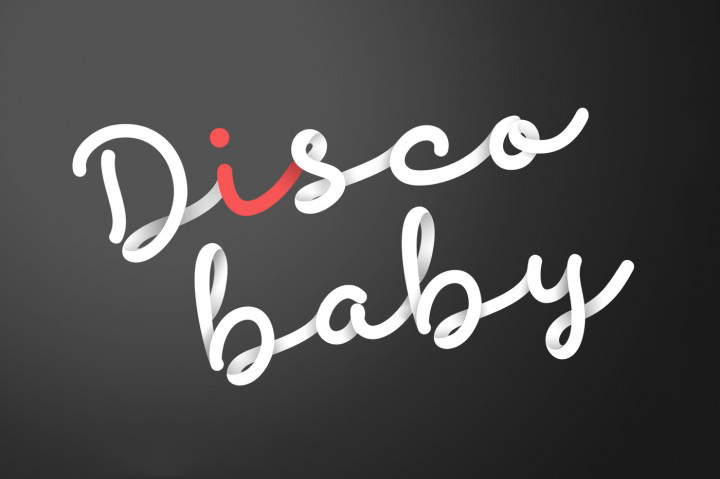
Discobaby Script Font – Download Grátis
A Discobaby Script Font é uma escolha perfeita para quem procura uma fonte script que traz aos designs um toque jovial e encantador sem perder a elegância necessária. Inspirada na forma quase infantil com que os pequenos escritam, essa fonte consegue criar um entusiasmo irresistível em qualquer design. Seja para o packaging de alimentos ou uma assinatura, desde logotipos até menus de entrada, Discobaby é uma opção versátil e encantadora. Suave e divertida, a Discobaby Script Font é perfeitamente adequada para estilos como marca, identidade visual, websites e elementos gráficos. Ela encaixa-se com perfeição em designs de produtos infantis ou roupas femininas que precisam de uma personalidade ativa e única. Seja qual seja o seu projeto design, a Discobaby Script Font é um recurso indispensável para criar um design vibrante e divertido.